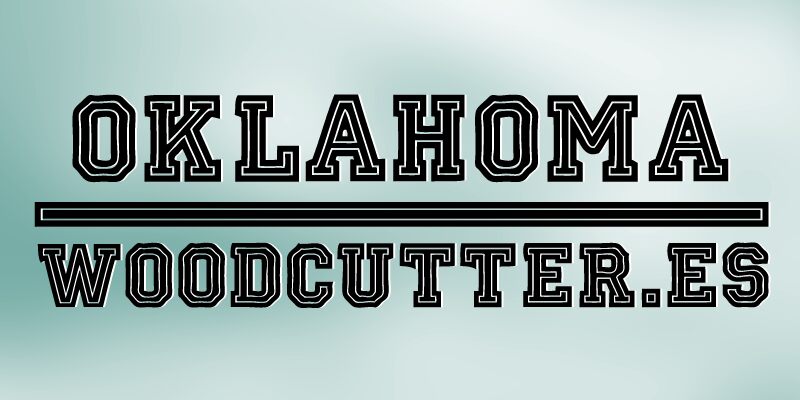
Oklahoma
Oklahoma od Woodcutter to darmowy krój displayowy z grubymi, blokowymi literami, podwójnym obrysem i strukturą w stylu «varsity», co nadaje mu wyrazisty, old-schoolowy charakter. Dzięki warstwowemu obrysowi, krój ten jest stworzony do dużych nagłówków, a nie drobnego tekstu, zapewniając każdemu słowu przejrzysty, graficzny rytm.
Ten darmowy font świetnie sprawdzi się w tytułach plakatów, brandingu sportowym, oprawie muzycznej, nadrukach na odzieży oraz logotypach w stylu vintage, gdzie potrzeba ciężkiego, wyrazistego kroju. Oklahoma pasuje również do oznakowań, ulotek eventowych i opakowań, które wymagają ostrego, uporządkowanego nagłówka bez utraty tego dobrze znanego, szkolnego klimatu.